13 font chữ tuyệt diệu nâng tầm thiết kế logo của bạn
Bạn đang tìm kiếm font chữ hoàn hảo cho dự án thiết kế logo của mình?
Chúng tôi đã chọn ra trong bài này 13 font chữ được ưa chuộng từ bộ sưu tập font chữ của HypeForType - trang web hàng đầu chuyên cung cấp các font chữ cao cấp cho lĩnh vực thiết kế. Mong rằng những font chữ đẹp mắt mà chúng tôi giới thiệu dưới đây sẽ giúp ích đắc lực cho công việc thiết kế của bạn.
01. Al Fresco by Laura Worthington
Sự tinh xảo và tươi tắn của font chữ Al Fresco mang lại nguồn cảm hứng dồi dào cho các chuyên gia thiết kế bộ nhận diện thương hiệu khi làm việc với các mẫu logo. Sự tinh tế và lãng mạn theo phong cách châu Âu đến từ những nét chữ thanh đậm khác duyên dáng. Nhà thiết kế Laura Worthington đã gọi đây là font chữ khó có thể cưỡng lại bởi sự tỏa sáng của nó.
02. Aracne Condensed by Antipixel
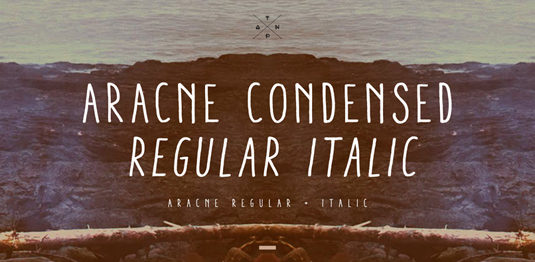
Bộ font chữ Antipixel có 4 độ rộng khác nhau, mang đến sự trình bày đa dạng, trong khi đó những chữ cái thon dài và quyến rũ lại gợi cảm hứng từ những bộ phim của Tim Burton và những chiếc quần jean mỏng nhất.
03. Bella by Face37
Bella mang cảm hứng cổ điển của Paris và New York trong một gói tải về. Độ rộng của chữ và những đườngcong thanh mảnh gợi phong cách vintage, trong khi khuôn tô chữ lại là một bài luyện tập hình học cho người dùng. Bạn sẽ muốn khám phá trọn vẹn vẻ đẹp của font chữ đẹp mắt này.
04. Breakers Slab by Kostic
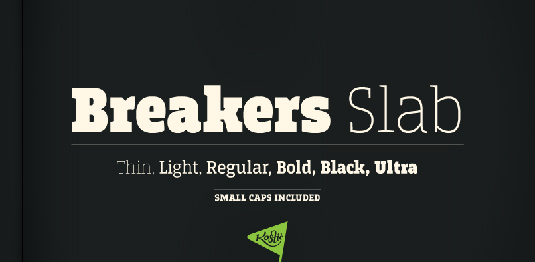
Font chữ tạo cảm hứng khi dùng để viết các tiêu đề lớn. Nó sẽ giúp tạo ra ấn tượng sâu sắc với thiết kế logo của bạn.
05. Etch by Produce
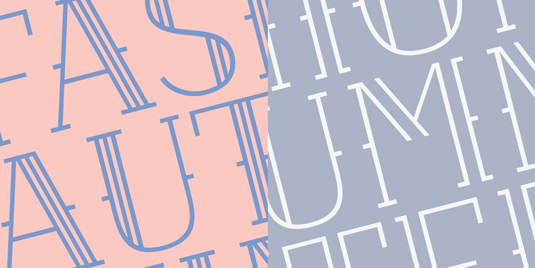
Các đường rãnh mỏng, đối xứng và có khoảng cách hoàn hảo là những đặc điểm ban đầu với font chữ này. Cũng giống như việc đi một chiếc thang máy trong khách sạn sang trọng, làm việc với font chữ này sẽ mang đến niềm vui và cảm hứng vintage ngay tức thì cho thiet ke logo của bạn.
06. Gauthier by Fontyou
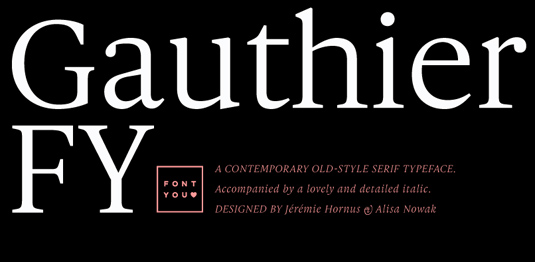
Một thiết kế tốt sẽ tồn tại bền vững với thời gian và font chữ mà bạn đang thấy có thể giúp thiet ke logo mà bạn đang làm trở nên ấn tượng hơn. Chiều cao của các chữ cái có thể kéo ra theo ý muốn để tạo các không gian trống cho 2 bên. Bạn sẽ sở hữu kiểu chữ in nghiêng thanh lịch cho logo của mình với font chữ này.
07. Lunetta by Sawdust
Mọi ký tự của font chữ mà bạn đang thấy đều chứa những khoảng rãnh đầy nghệ thuật, cách sử dụng đường nét rất khéo léo. Còn điều gì ấn tượng hơn nếu kết hợp font chữ sáng tạo này vào logo của bạn?
08. Muirside by Steven Bonner
Font chữ thú vị này mang lại cảm giác gần gũi như trong những ngôi nhà ở thành thị. Nó có thể được dùng cho logo của các hãng bán đồ cho nam giới, cửa hàng văn phòng phẩm.
09. Otto by Non-Format
Font chữ kỳ diệu này tạo ra bởi Non Format Studio. Nhiều thiết kế logo của các hãng lớn đã sử dụng font chữ này, chẳng hạn như Nike, Orange, Uniqlo ...Font chữ độc đáo ấy là sự kết hợp của những đường nét tinh tế và khối màu sẽ mang lại cảm hứng thiết kế cho bạn.
10. Port by Joao Oliveira
Bạn sẽ thỏa sức áp dụng font chữ ấn tượng này vào nhiều lĩnh vực khác nhau. Các nét thanh và đập cùng đường nét uyển chuyển của font chữ này sẽ làm nên sức quyến rũ khó cưỡng lại của logo nào sử dụng nó.
11. Sobek by Thinkdust
Các góc nhọn và đường cong làm nên một font chữ có một không hai. Mỗi chứ cái là một sự sáng tạo thành công và việc kết hợp các chữ cái với nhau thành một từ hoặc cụm từ có ý nghĩa trên logo sẽ mang lại vẻ hiện đại cho logo đó.
12. Thirsty Rough by Yellow Design Studio
Kỹ thuật làm xỉn màu chữ lại khiến cho font này trở nên gần gũi và thân thiện. Các chi tiết của chữ sẽ trở nên rõ ràng hơn nếu bạn sử dụng nó ở kích thước to.
13. TJ Evolette A by TypeMe
TJ Evolette A mang diện mạo hiện đại và sẵn sàng để xuất hiện trên các mẫu logo như điểm nhấn chính. Bạn có thể sắp xếp các chữ cái theo một chuối có trật tự hoặc sắp xếp một cách phá cách theo ý muốn trên logo. Bộ font chữ sẵn sàng để bạn thực hiện những ý tưởng hướng dẫn thiết kế logo đa dạng.